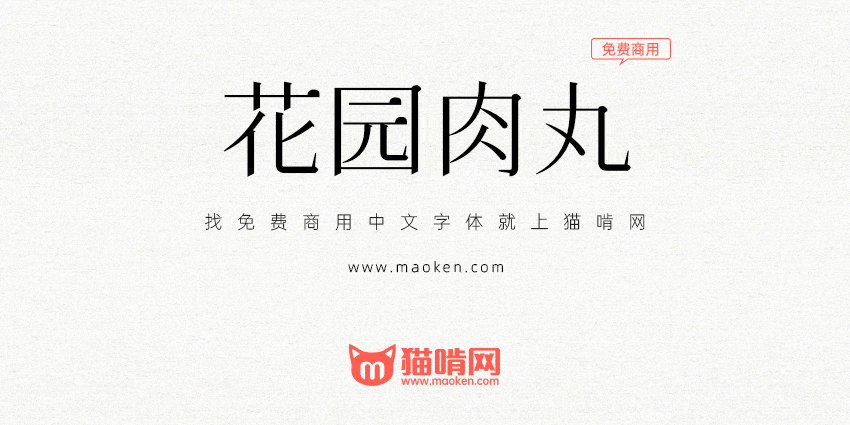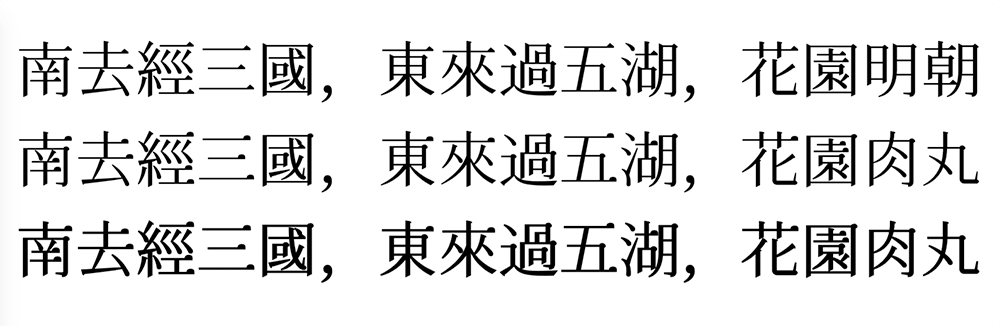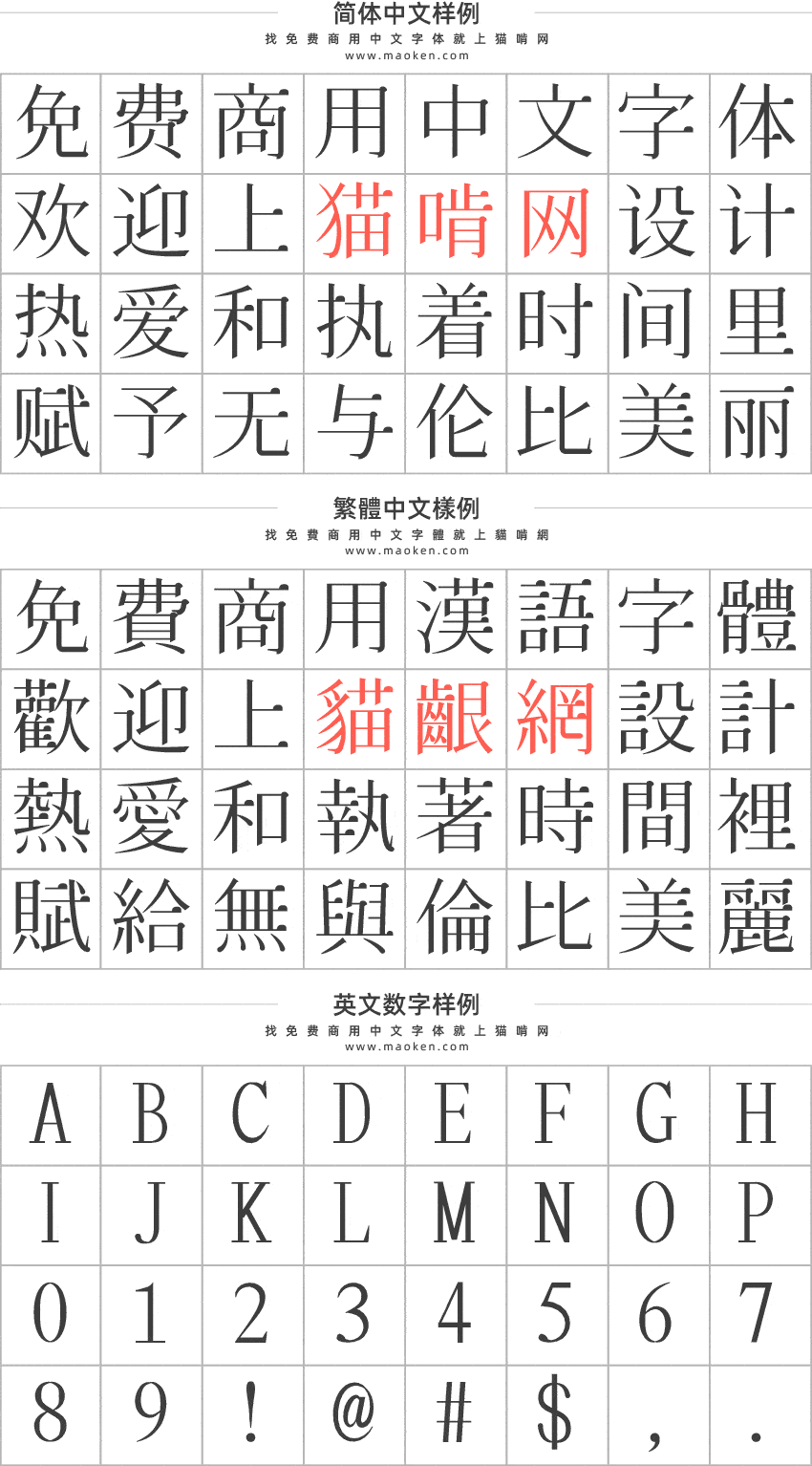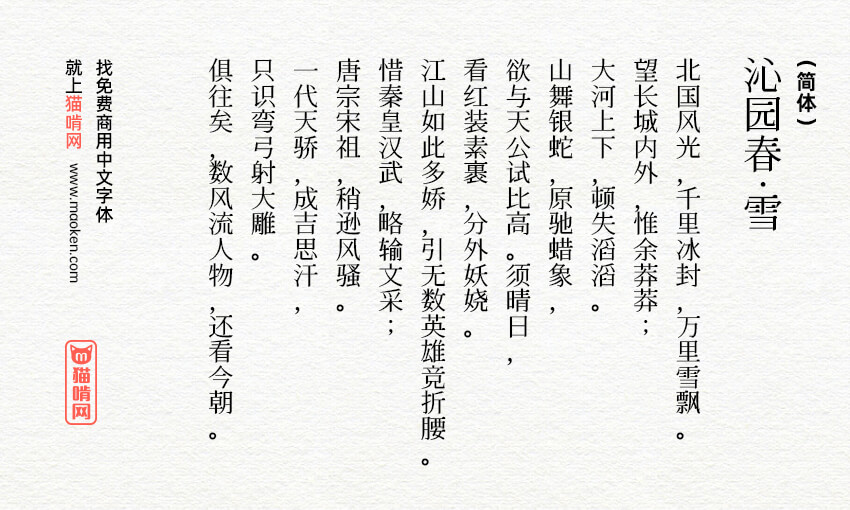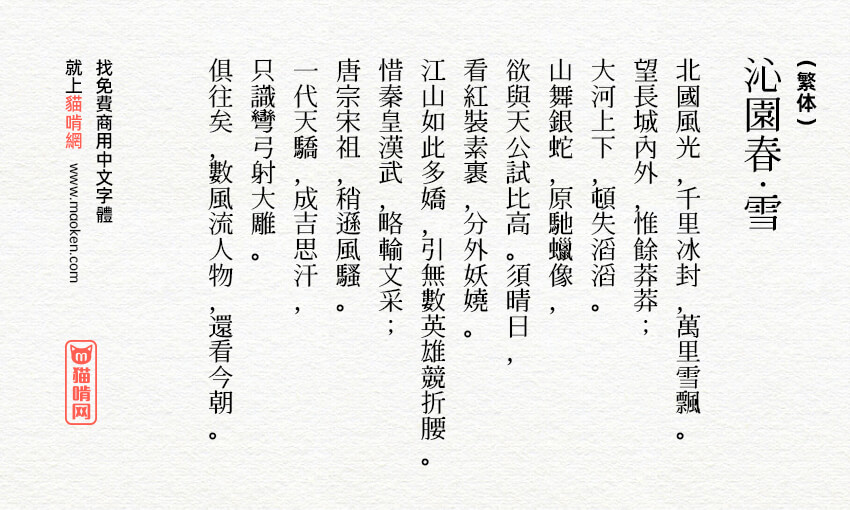
花园肉丸字体是使用“狮尾肉丸”字体的转换程序,套用到“花园明朝”字体后得出的字体,发现效果还挺不错的的。花园肉丸字体基于花园明朝的转角的三角形转成半圆形改造,是一款游走于古典与可爱之间的字体。欢迎大家自由应用、自由优化、自由改作!
附注:花园肉丸的Regular字重,是直接来自花园明朝,而Medium字重是透过程序产生,不能确定所有的字都正常,可能某些字会转换失败。大家在使用的时候请检查一下哦。